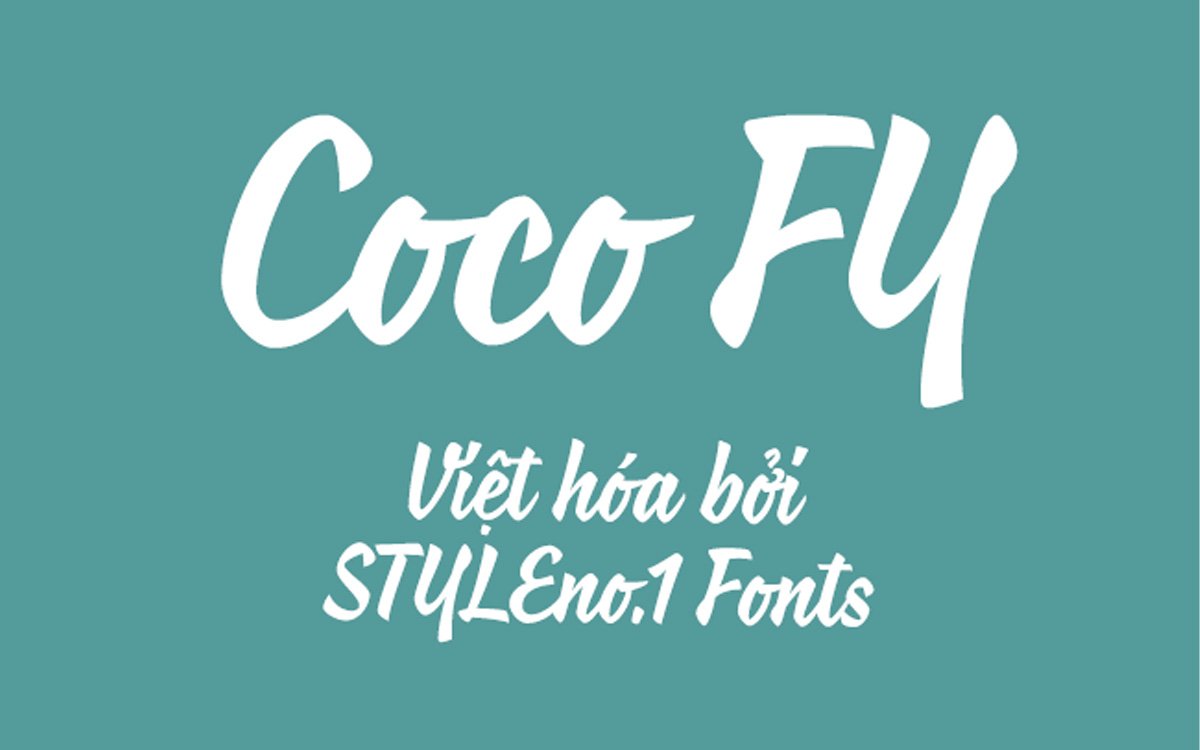
Font chữ mềm mại SVN-Coco FY
Trong thế giới thiết kế đồ họa hiện đại, việc lựa chọn một phông chữ phù hợp không chỉ giúp truyền tải thông điệp một cách rõ ràng mà còn định hình phong cách nghệ thuật độc đáo cho toàn bộ tác phẩm. Font chữ mềm mại SVN-Coco FY chính là sự kết hợp hoàn hảo giữa nét đẹp lãng mạn, cổ điển và tính ứng dụng linh hoạt trong các dự án sáng tạo đương đại. Được Việt hóa tỉ mỉ bởi nhóm tác giả SVN, bộ font này đã và đang trở thành trợ thủ đắc lực cho các designer trong hành trình tạo dựng bộ nhận diện thương hiệu, bao bì sản phẩm hay ấn phẩm truyền thông độc đáo.
Khám Phá Font Chữ Mềm Mại SVN-Coco FY – Giải Pháp Typography Đẳng Cấp Cho Thiết Kế Việt
SVN-Coco FY vốn được phát triển dựa trên nguyên bản Coco FY – một tác phẩm typography nổi tiếng mang đậm phong cách vintage và nét duyên dáng phương Tây. Khi được tiến hành Việt hóa, phông chữ này giữ nguyên trọn vẹn những đường uốn lượn quyến rũ, đồng thời được tối ưu hóa hệ thống dấu tiếng Việt để mang lại sự hài hòa về mặt thị giác. Nhu cầu sử dụng các kiểu chữ mang tính nữ tính, thanh lịch và nghệ thuật đang tăng cao trong các ngành công nghiệp sáng tạo như thời trang, mỹ phẩm, tổ chức sự kiện và thiết kế nội thất. Sự xuất hiện của SVN-Coco FY đáp ứng trọn vẹn mong muốn sở hữu một bộ phông chữ vừa mang tính thẩm mỹ cao, vừa chuẩn SEO và dễ dàng tương thích với thị trường Việt Nam.
Không giống như các font chữ sans-serif góc cạnh hay serif truyền thống có phần cứng nhắc, font chữ mềm mại SVN-Coco FY thổi một làn gió tươi mới vào các bản thiết kế nhờ cấu trúc nét chữ mềm mại, bay bổng. Việc nắm rõ các tính năng cũng như cách ứng dụng kiểu chữ này sẽ giúp bạn nâng tầm giá trị hình ảnh cho mọi sản phẩm truyền thông.
1. Đường Nét Thiết Kế Mềm Mại, Uốn Lượn Và Tinh Tế
Điểm đặc trưng đầu tiên thu hút người xem của SVN-Coco FY chính là hệ thống đường nét được chế tác cực kỳ công phu. Nét chữ có độ tương phản vừa phải giữa các đường nét đậm và mảnh, tạo nên hiệu ứng thị giác uyển chuyển nhưng vẫn đảm bảo sự vững chắc cho bố cục văn bản.
Các đường cong của font chữ được xử lý mượt mà, gợi liên tưởng đến những nét bút calligraphic thủ công sang trọng. Nhờ đặc điểm này, SVN-Coco FY dễ dàng tạo cảm giác gần gũi, tinh tế và ấm áp cho người xem. Đây là sự lựa chọn lý tưởng cho các dòng tiêu đề (heading) cần thu hút sự chú ý lập tức trên banner quảng cáo, poster hay trang bìa tạp chí.
• Độ tương phản nét chữ: Tạo chiều sâu và vẻ đẹp quý phái.
• Đường cong tự nhiên: Mang lại cảm giác mượt mà, không bị gượng ép.
• Phong cách chủ đạo: Vintage, Romantic, Elegant và Modern Script.
2. Hỗ Trợ Tiếng Việt Trọn Vẹn Cùng Hệ Thống Glyph Phong Phú
Một trong những rào cản lớn nhất của các designer Việt Nam khi sử dụng font quốc tế là tình trạng lỗi dấu hoặc dấu tiếng Việt bị lệch tông so với tổng thể nét chữ. Phiên bản SVN-Coco FY đã giải quyết triệt để vấn đề này nhờ quá trình Việt hóa chuẩn mực.
Hệ thống dấu tiếng Việt trong SVN-Coco FY được căn chỉnh khoảng cách (kerning) và tỷ lệ cẩn thận, đảm bảo không làm mất đi vẻ mềm mại nguyên bản của bộ font. Bên cạnh đó, phông chữ còn đi kèm với hệ thống ký tự thay thế (alternate glyphs) và các nét nối (ligatures) phong phú, cho phép người dùng tùy biến thiết kế theo nhiều biến thể độc đáo khác nhau mà không lo đụng hàng.
1. Tích hợp đầy đủ 29 chữ cái tiếng Việt cùng hệ thống dấu thanh chuẩn xác.
2. Cung cấp nhiều ký tự đặc biệt và biểu tượng trang trí đi kèm.
3. Hỗ trợ tính năng OpenType giúp dễ dàng chèn các ký tự thay thế trong Adobe Illustrator hoặc Photoshop.
3. Tính Ứng Dụng Đa Dạng Trong Thiết Kế Đồ Họa Hợp Xu Hướng
Nhờ tính linh hoạt trong thẩm mỹ, font chữ mềm mại SVN-Coco FY không bị giới hạn ở một lĩnh vực nhất định mà có thể tỏa sáng trong vô số dự án sáng tạo khác nhau. Từ những thiết kế mang tính cá nhân đến các dự án nhận diện thương hiệu doanh nghiệp lớn, kiểu chữ này đều phát huy tối đa công năng.
Đối với ngành thiết kế bao bì, SVN-Coco FY thường được ứng dụng trên các nhãn hiệu nước hoa, mỹ phẩm cao cấp, trà hoa, nến thơm hoặc các sản phẩm handmade. Nét chữ quyến rũ giúp tôn vinh giá trị sản phẩm và thu hút nhóm khách hàng yêu thích sự tinh tế. Đối với lĩnh vực sự kiện, đây là lựa chọn hàng đầu cho thiệp cưới, thiệp mời sự kiện thượng lưu, menu nhà hàng phong cách Âu hay các bảng hiệu trang trí.
• Nhận diện thương hiệu: Thiết kế logo, tagline, brochure cho spa, thẩm mỹ viện, thương hiệu thời trang nữ.
• Ấn phẩm sự kiện: Thiệp cưới, thư cảm ơn, thiệp sinh nhật, giấy mời VIP.
• Truyền thông số: Tạo hình ảnh quote nghệ thuật, banner Facebook, Instagram Story, thumbnail Youtube.